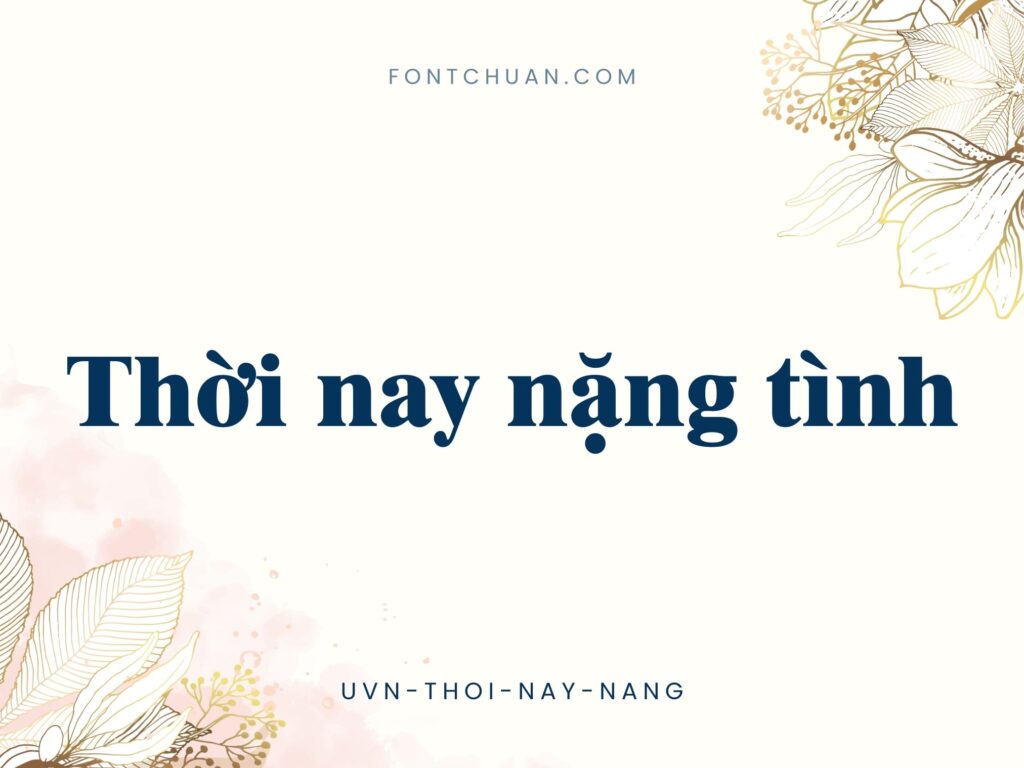
Font UVN Thoi Nay Nang Việt Hóa
UVN Thời Nay Nặng là một kiểu chữ ấn tượng với cấu trúc mạnh mẽ, đậm nét và mang phong cách hiện đại hóa từ các mẫu chữ cổ điển. Font thuộc bộ sưu tập của nhóm UVN, mang lại cảm giác chắc chắn và nổi bật trong từng ký tự. Với thiết kế các đường nét vuông vức, đều đặn và dày, UVN Thời Nay Nặng đặc biệt hiệu quả khi dùng làm tiêu đề, nhấn mạnh thông điệp trong thiết kế. Dù không rõ tên tác giả cụ thể, font này đã được cộng đồng thiết kế Việt đón nhận nhờ tính ứng dụng cao và khả năng hiển thị rõ ràng. Font này chỉ được sưu tầm và đăng bởi thành viên của Font Chuẩn, phục vụ nhu cầu sử dụng trong các dự án thực tế về truyền thông, thiết kế thương hiệu và quảng cáo.
Với độ nặng rõ rệt, UVN Thời Nay Nặng đem đến sự tương phản mạnh, tạo điểm nhấn trong bố cục. Các đường nét được tối ưu hóa để đọc tốt ở kích thước lớn, phù hợp với các bảng quảng cáo, poster, banner hoặc tiêu đề website. Bộ font đặc biệt hữu ích trong lĩnh vực bất động sản, công nghệ, giáo dục, hoặc các sản phẩm in ấn cần sự chắc chắn và hiện đại. Đồng thời, font cũng phù hợp với các chiến dịch truyền thông dịp lễ hội, sinh nhật hoặc các dịp đặc biệt khác.